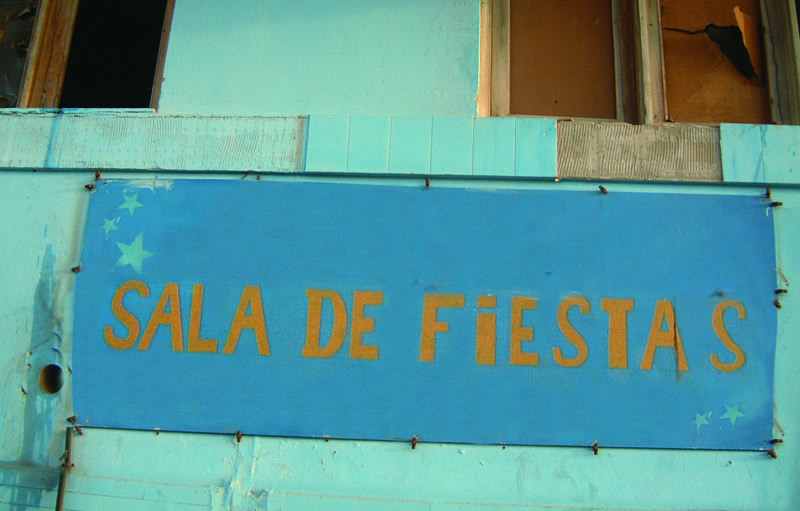
Sala de Fiestas von Studio KMzero ist eine kostenlose Cartoon-Display-Schrift mit kräftigen, unregelmäßigen Buchstaben. Breite Rundungen und ungleichmäßige Strichstärken verleihen den Formen eine handgeschnittene Anmutung. Die Formen sind weich, aber ausdrucksstark.
Sie kann einen Titel in einen Teil einer verspielten, illustrierten Szene verwandeln. Dieser Ansatz eignet sich für Kinderposter, Partyinladungen und Snack-Verpackungen, besonders wenn das Design übergroße Formen bevorzugt. Ihre abgerundeten Silhouetten können an Luftballons, Papierschnitte oder andere markante Illustrationen erinnern, anstatt sich wie neutraler Text zu verhalten.
Sala de Fiestas wurde von einem handgemalten Schild für einen Ballsaal auf der Insel Fuerteventura inspiriert. Fehlende Buchstaben wurden so gezeichnet, dass sie zu den Merkmalen der bestehenden Buchstaben passten, einschließlich lockerer Serifen und sternförmiger Punkte.